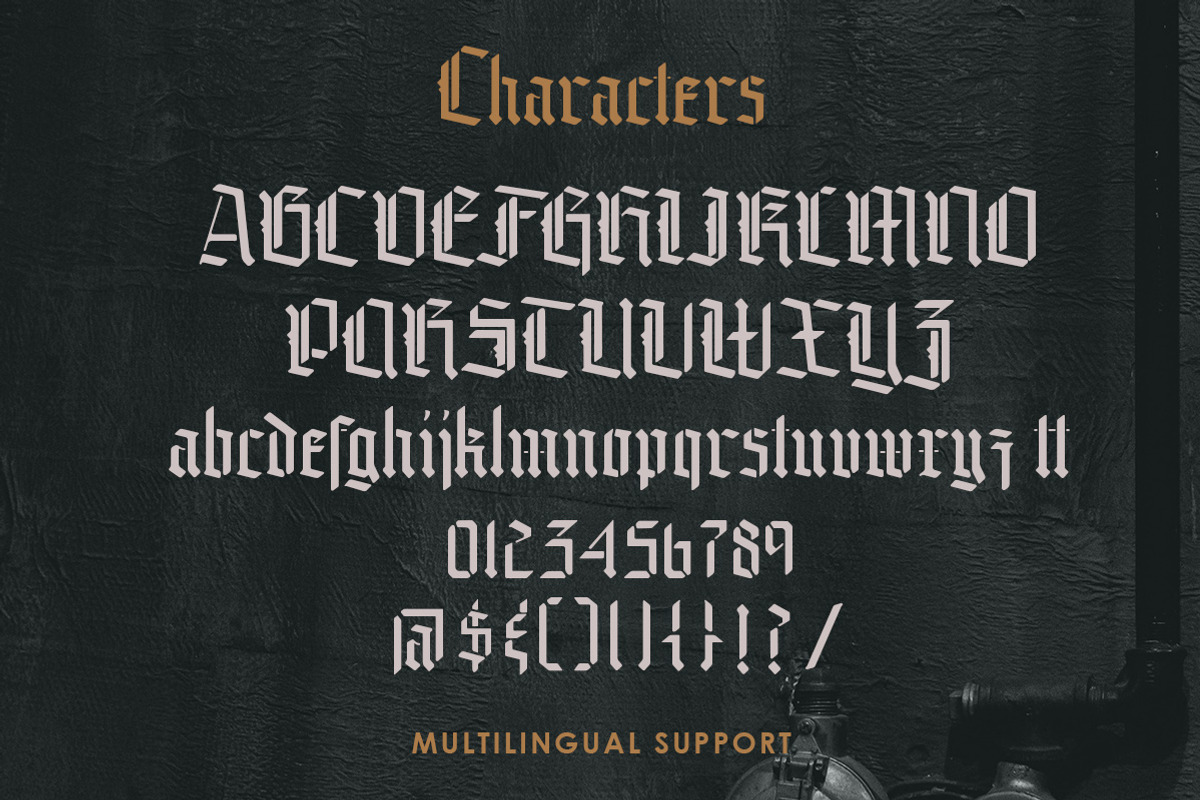
Fraktur-Schablonenschrift?
ich suche gerade eine Fraktur-Schablonenschrift. Die einzige die ich bislang finden konnte, ist die „Kuschelfraktur“ (hier in den Fontlisten) – gefällt mir gut, aber mir schwebt eine Schrift ohne Pinselstrich-Duktus vor, die stärker „frakturiert“ wirkt, also kantiger / geradliniger. Fällt da jemanden zufällig noch was ein?
Ich bin gerade noch über diese hier gestolpert:
Die Schrift ist schablonenfähig und gebrochen. Aber eine stenciled Fraktur ist es nicht. Ralfs Vorschlag, die Vtg Stencil Germany No. 101 von Andreas, ist wahrscheinlich schon der beste Treffer.
Aber die hat doch gerade den Pinselstrich-Duktus, den Tillt nicht möchte … ?
Ich denke, da meint er den besonderen Look der Kuschelfraktur, nicht die Bandzugfeder …
@Thomas Kunz, danke für den Tipp, die „Tannen Stencil“ sieht interessant aus, auch wenn es keine Fraktur ist – auf jeden Fall ist sie explizit nicht kuschelig. :lol:
@Diwarnai und @Norbert P gemeint war in der Tat der  Look der „Kuschelfraktur“.